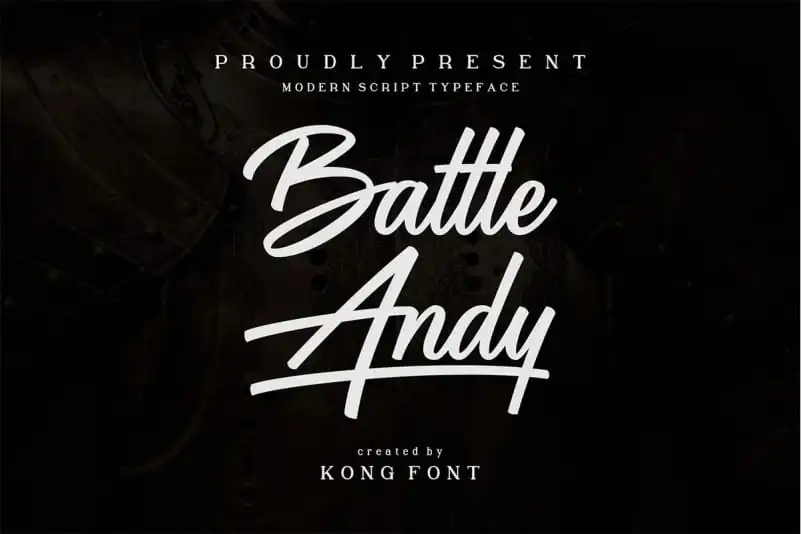
Battle Andy Script Font é uma fonte tipográfica desenhada com leveza e fluidez, perfeita para aqueles projetos que exigem um toque pessoal e criativo. Desenvolvida pelo font designer Kong Font, esta font pode ser usada em uma ampla variedade de projetos, tornando-os ainda mais notáveis e memoráveis. Esta font se destaca por sua versatilidade inigualável, adequada para estilos diversos e possuindo um design que complementa com perfeição a maioria dos esquemas gráficos. Quando adicionada aos seus projetos mais imaginativos, você sentirá como esta font tem uma personalidade própria, capaz de fazer os seus trabalhos se destacarem ainda mais. Inclua Battle Andy Script Font em seu inventário de recursos gráficos e note o impacto transformador que ela pode ter. Esta é a fonte perfeita para quem procura um toque único, um visual moderno e uma habilidade incrivelmente versátil para seus projetos mais criativos.